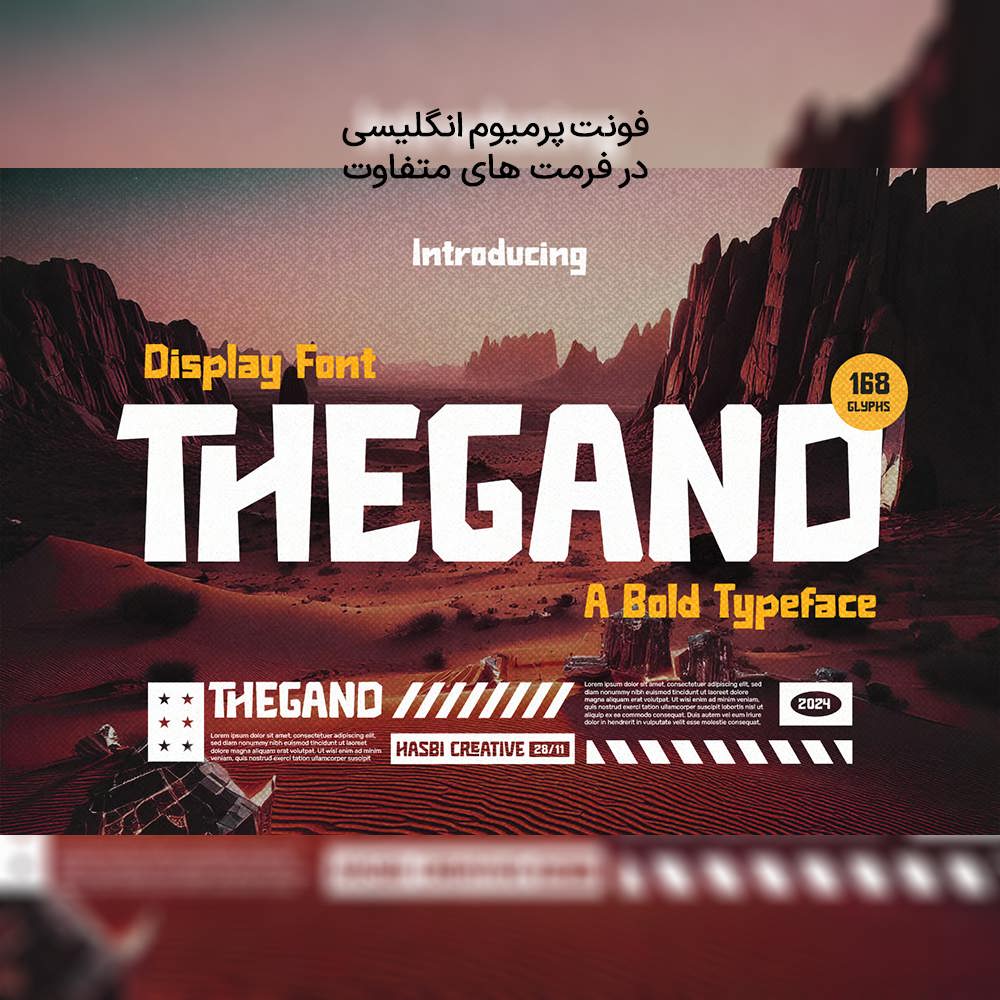
دانلود فونت انگلیسی Thegand Font
فونت پرمیوم و انگلیسی Thegand Font یک فونت جسورانه، انتزاعی و دستساز است که به عناوین و تیترها شخصیت و خلاقیت میبخشد. این فونت که برای پوسترهای فیلم، رسانههای اجتماعی و برندسازی در صنایع غذایی، ورزشی و خودروسازی ایدهآل است، با خطوط دستساز و منحصر به فرد خود، سبکی پویا و رسا ارائه میدهد و میتواند در پروژههای خلاقانه مختلفی که به دنبال یک سبک منحصربهفرد و چشمنواز هستند استفاده شود.
مزایای استفاده از فونت لاتین Thegand Font چیست؟